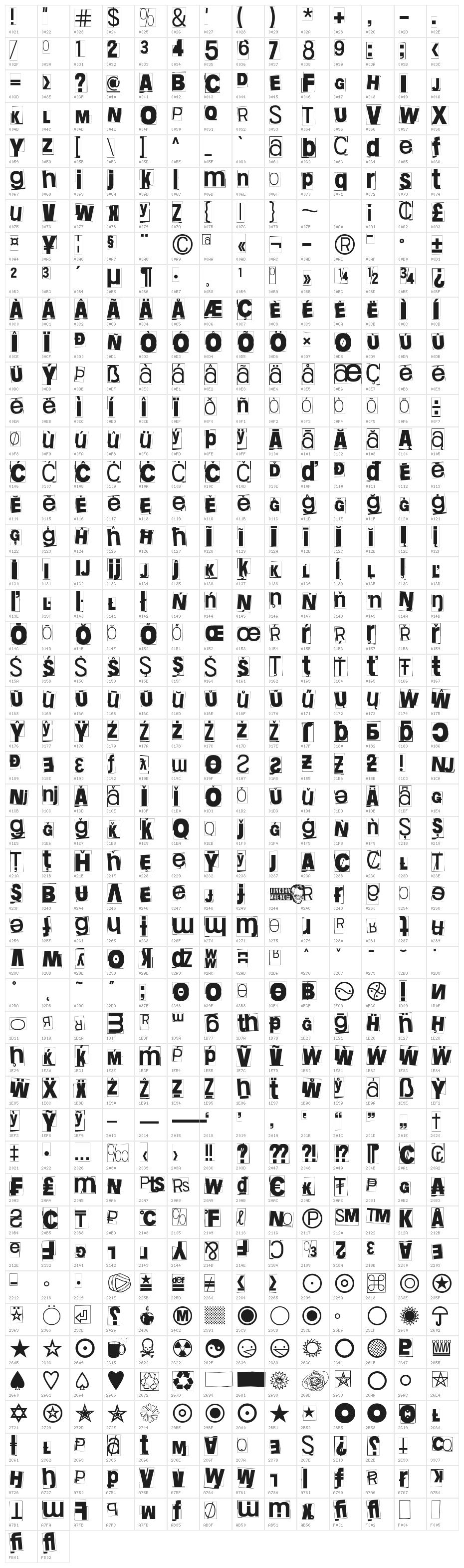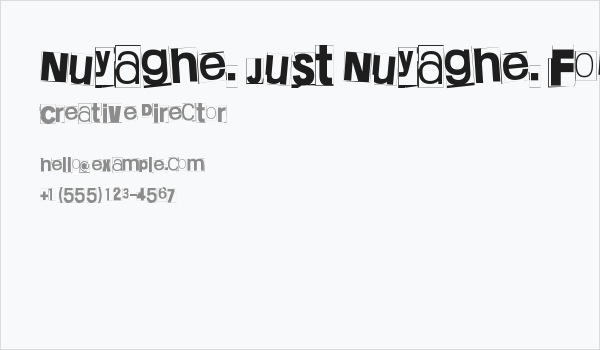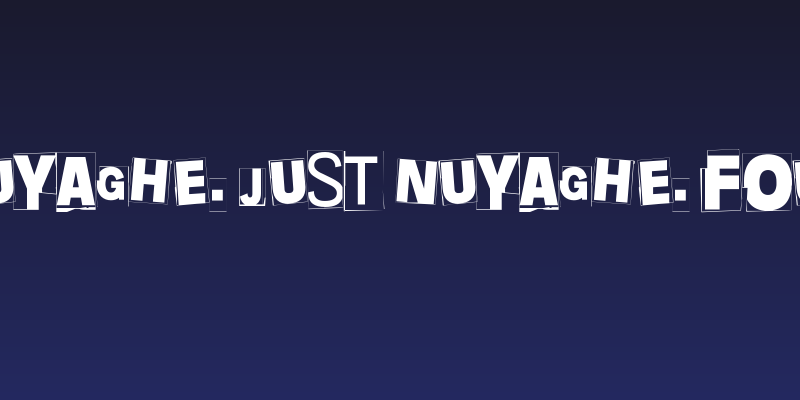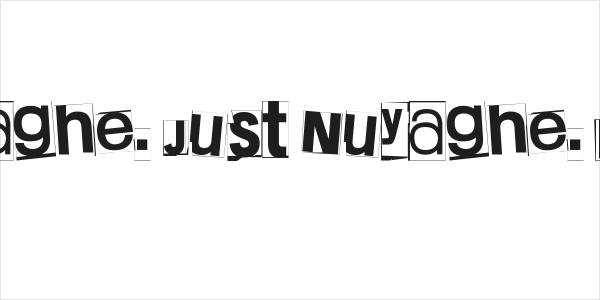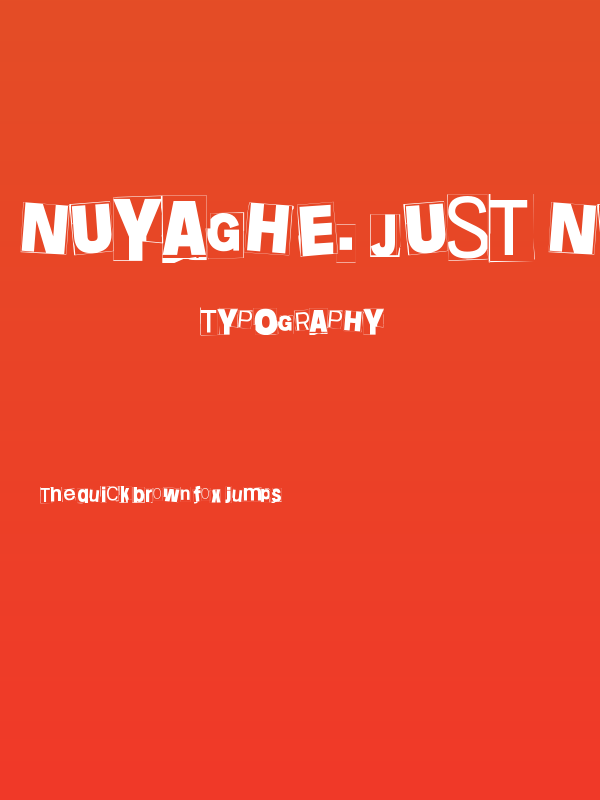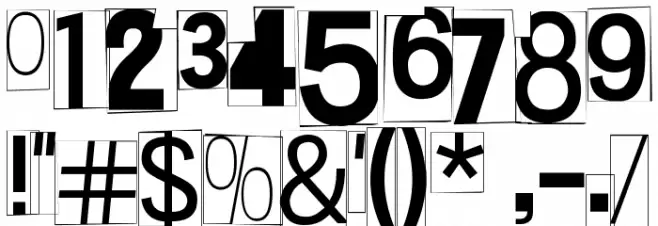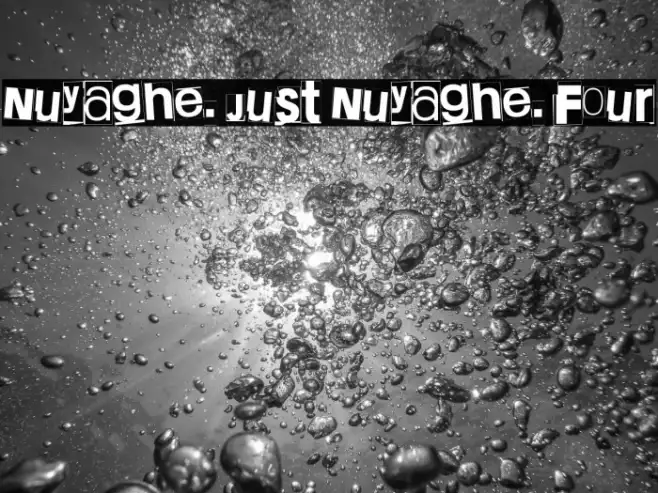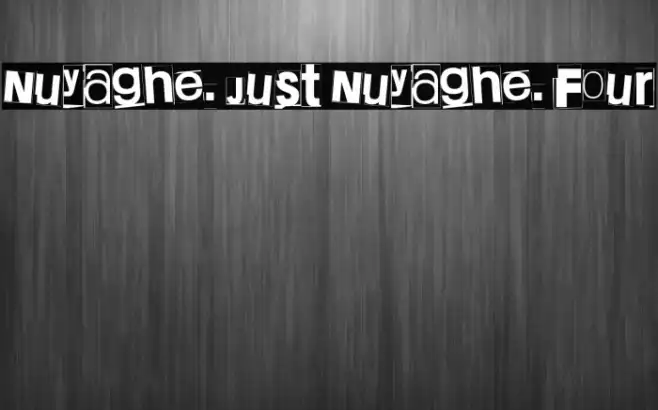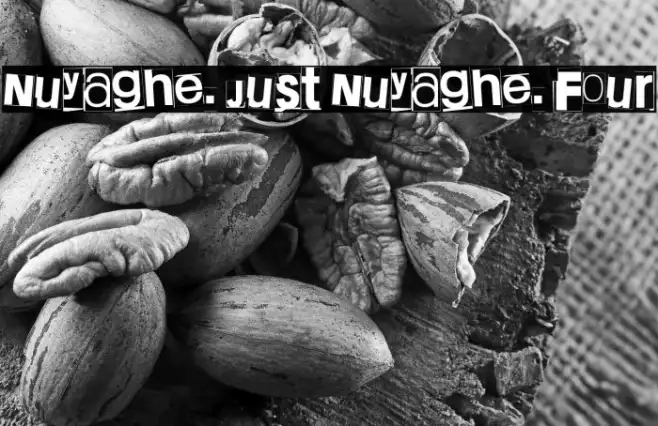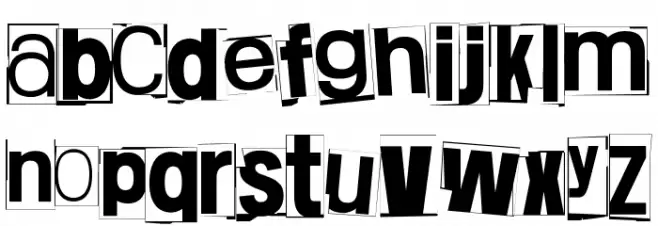
Nuyaghe. Just Nuyaghe. Four Font
| Anwendungsfall | Headlines, Logos, Artistic projects |
| Vorgeschlagene Projekte | Ideal for posters, album covers, artistic projects, and any design requiring a bold, unconventional look. |